ปกติดีไซเนอร์จะมีฟอนต์ให้เลือกใช้สำหรับออกแบบหลายตระกูล แต่ใช่ว่าการออกแบบฟอนต์จะต้องมาจากการวาดเขียนเสมอไป ลองมาดูกันว่านอกจากฟอนต์ธรรมดาที่เราใช้แล้ว ถ้าโลกนี้ไม่มีกระดาษปากกาหรือไม่ใช้นิ้วเขียน เราจะสร้างสรรค์ฟอนต์จากอะไรได้อีก
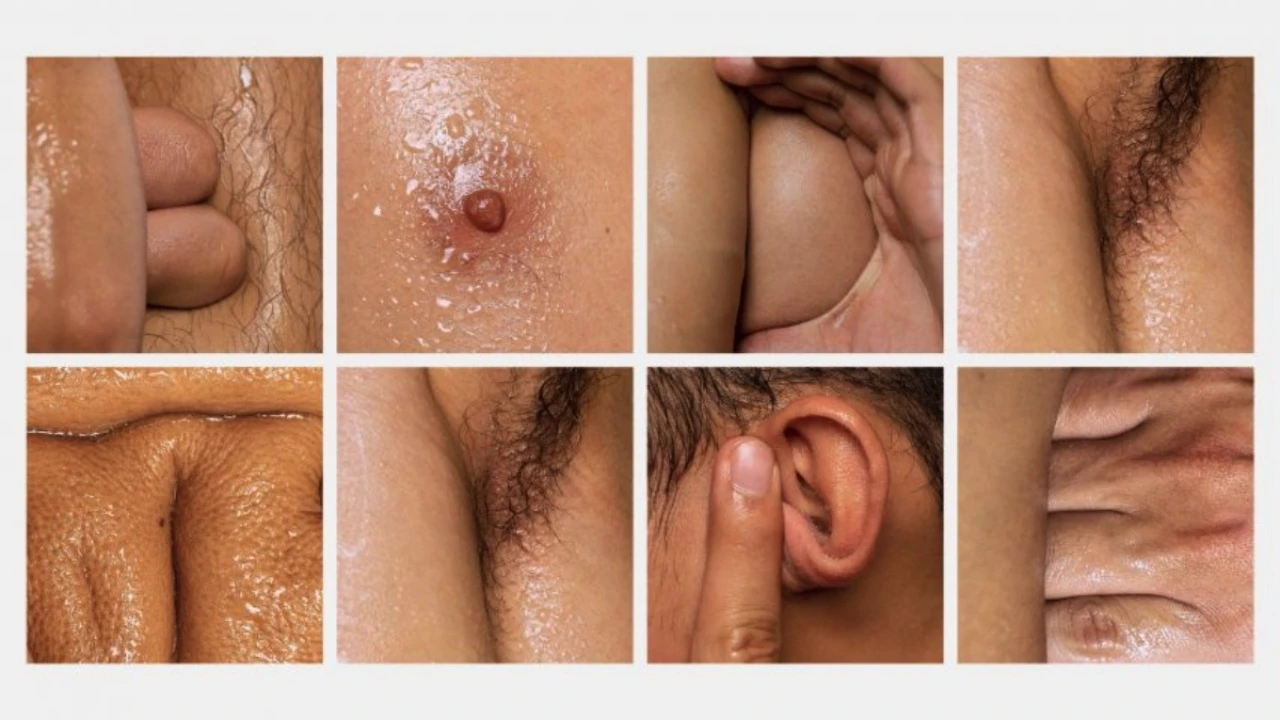
Body Type
เริ่มฟอนต์แรกจาก Julius Raymund Advincula กราฟิกดีไซเนอร์ชาวฟิลลิปปินส์ที่ตอนนั้นเขากำลังเข้าร่วมชาเลนจ์ในโปรเจกต์ 36 Days of Type challenge (โปรเจกต์ที่ว่าด้วยการออกแบบตัวอักษรหรือตัวเลขต่อเนื่องกันใน 36 วัน) ระหว่างที่คิดว่าจะทำอะไรดี พอเข้าไปดูผลงานคนอื่นก็เห็นว่าดีไซน์ส่วนใหญ่เป็นงานวาดสายภาพประกอบกับงานเชิงดิจิทัล ด้วยความอยากฉีกจากคนอื่นก็ปิ๊งคอนเซ็ปต์ในหัวขึ้นมาเป็น ‘Body type’ จาก ‘Body language’ ซึ่งวิธีทำฟอนต์จาก Body Type คือการที่เขาสเปรย์น้ำมันลงบนผิว นั่งเปลือยหน้ากระจกแล้วสำรวจหาฟอนต์จากรอยพับหรือฟอร์มอวัยวะของตัวเอง
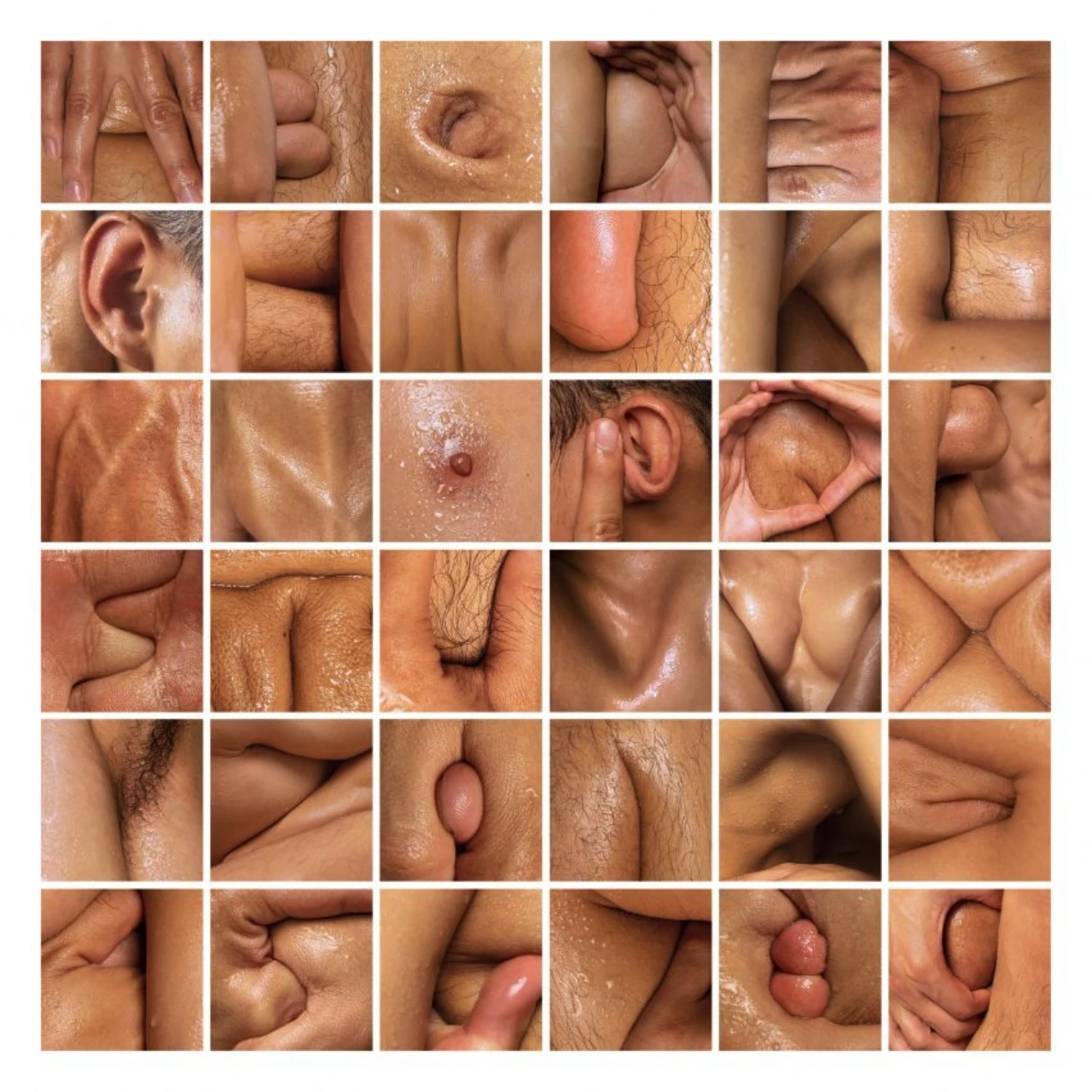
Alphabets & Number – Julius Raymund Advincula
งานนี้มีตัวเขาเป็นแบบและมีผู้ช่วยที่คอยจัดท่ากับถ่ายภาพเก็บแต่ละฟอนต์ไว้ ส่วนเรื่องทำไมต้องสเปรย์น้ำมันก่อนถ่าย เขาให้คำอธิบายว่ามันช่วยเรื่องแสงเงา เติมความเป็นธรรมชาติให้กับผิวส่วนที่นูน แง่การใช้งานเราว่าฟอนต์ชุดนี้ไม่เหมาะกับข้อความยาวๆ แต่ถ้าเอาไปใช้ในเชิงสัญลักษณ์ เล่นกับการสื่อสารแนว Puzzle หรือ Text หากันแนว Sexual ก็ดูจะเป็นไอเดียที่เข้าท่า เพราะดีไซน์มันสร้างมู้ดได้ดี
Hair Typography
ฟอนต์เส้นผมที่มองว่าสวยก็ใช่ สยองก็ได้ ออกแบบโดย Monique Goossens อาจารย์สอน Interior Design and Visual Communication ฟอนต์นี้เกิดจากความตั้งใจที่เขาอยากให้มันนำไปใช้บน Magazine ปกหนังสือ และสร้างคอมมิชชั่นไว้เป็นค่าขนมส่วนตัว
วิธีสร้างฟอนต์เขาใช้การเรียงต่อและพันกันของผมหลายๆ เส้นมาบิด พัน หรือวางซ้อน ให้ช่วงกลางฟอนต์มีความหนาอ่านง่าย ส่วนปลายจะมีความยุ่งๆ แตกๆ ตามสไตล์ธรรมชาติของเส้นผมหน่อยแล้วถ่ายภาพไว้ ถ้ามองเทียบกับฟอนต์อื่นในซีรีส์ร่างกายที่เอามาฝาก ฟอนต์นี้จัดว่าอ่านง่ายและน่าจะใช้งานได้ง่ายที่สุด
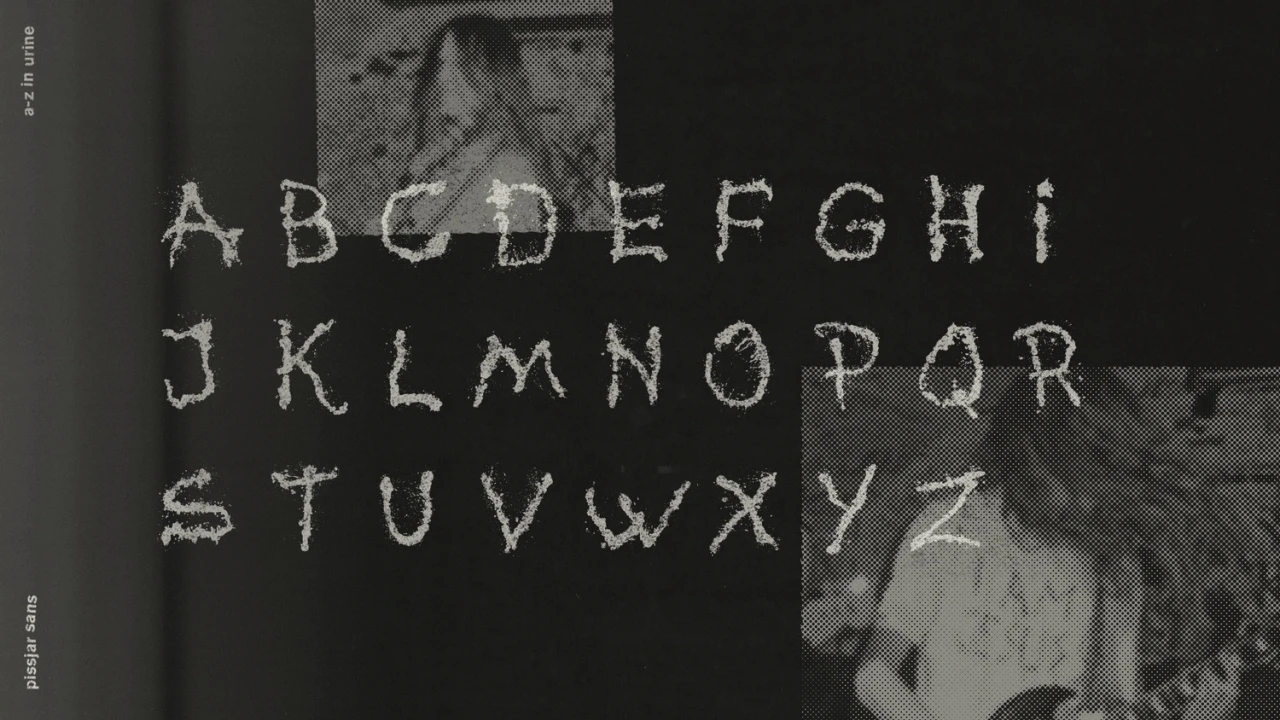
PISSJAR Sans
ปิดท้ายด้วยฟอนต์สุดห่ามที่เขาใช้วิธียิงกระต่ายสร้างสรรค์ฟอนต์! ดีไซเนอร์งานนี้คือวงพังก์ชาวสวีเดนที่ออกแบบฟอนต์สำหรับปกวง (Record Sleeve) ด้วยการให้สมาชิกวงยิงกระต่ายหรือปัสสาวะใส่ผ้าปูที่นอนที่ขึงไว้ตึงๆ ให้เป็นตัวอักษร จากนั้นถ่ายภาพแล้วใช้โปรแกรมทำเวกเตอร์ดึงรอยหยดส่วนเกินออก เก็บไว้เฉพาะตัวที่อ่านเป็นฟอนต์ได้ชัดๆ ฉะนั้นเรื่องความแม่นจึงไม่เป็นอุปสรรค
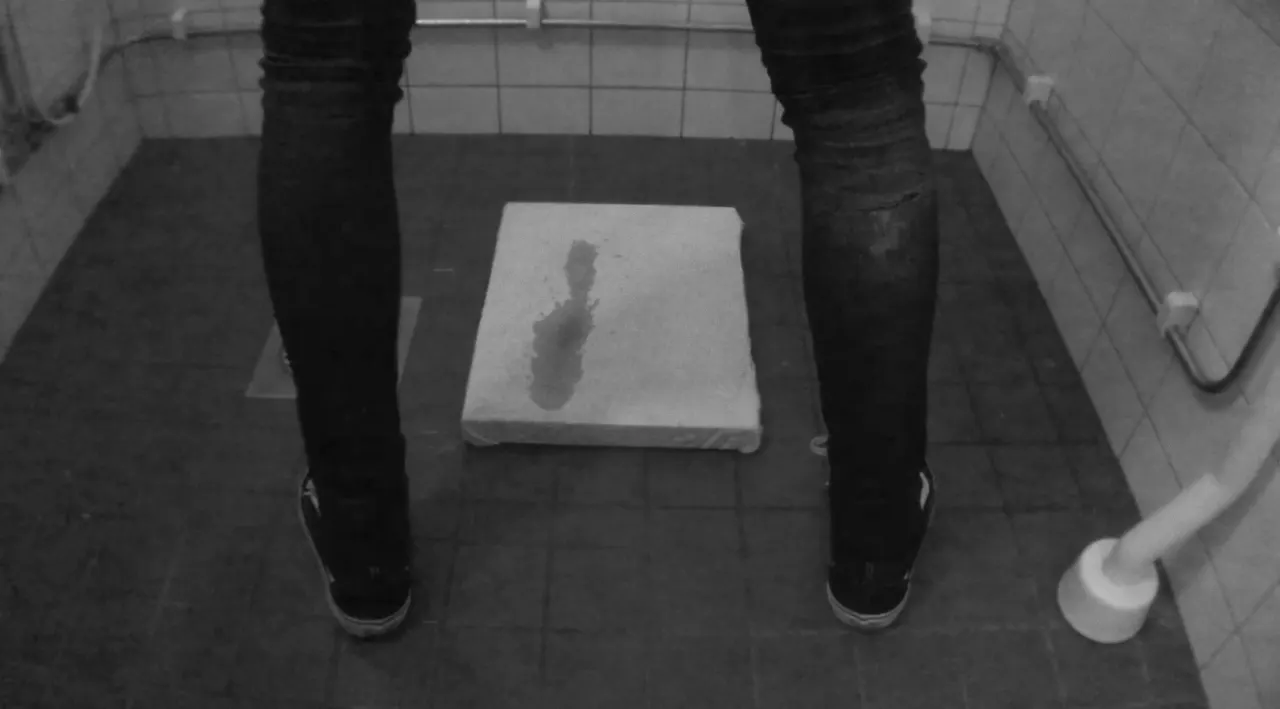
- เฟรมพร้อมยิง! –
- ผลงาน Ori ตัว ‘J’ –
คอนเซ็ปต์การออกแบบครั้งนี้เขาบอกว่าเป็น “the dirty hardcore punk that we play.” ใครอยากรู้ว่าเพลงมันส์ขนาดไหนถึงดีไซน์ปกวงด้วยฟอนต์แบบนี้ เข้าไปค้นหาอัลบั้ม Apathy & Cheap Thrills ฟังดูได้ ส่วนใครอยากโหลดไปใช้เอามันส์ ฟอนต์นี้เป็นฟอนต์เดียวที่เขาก็เปิดให้โหลดใช้ฟรีแล้วในนี้